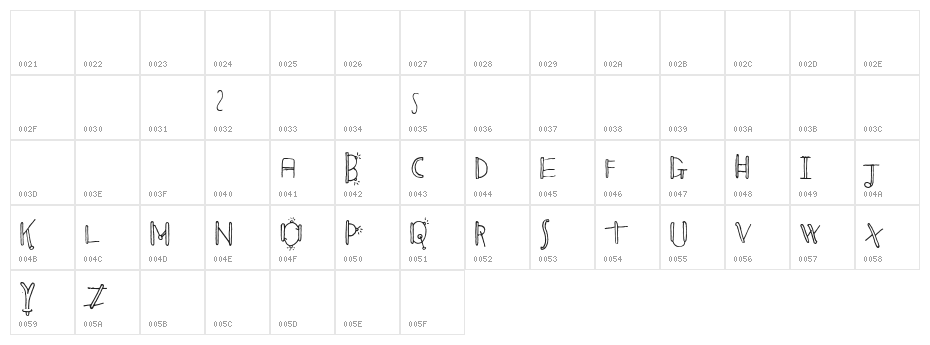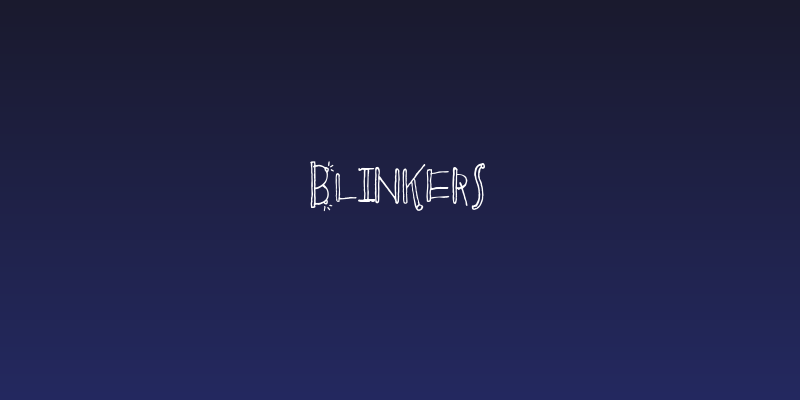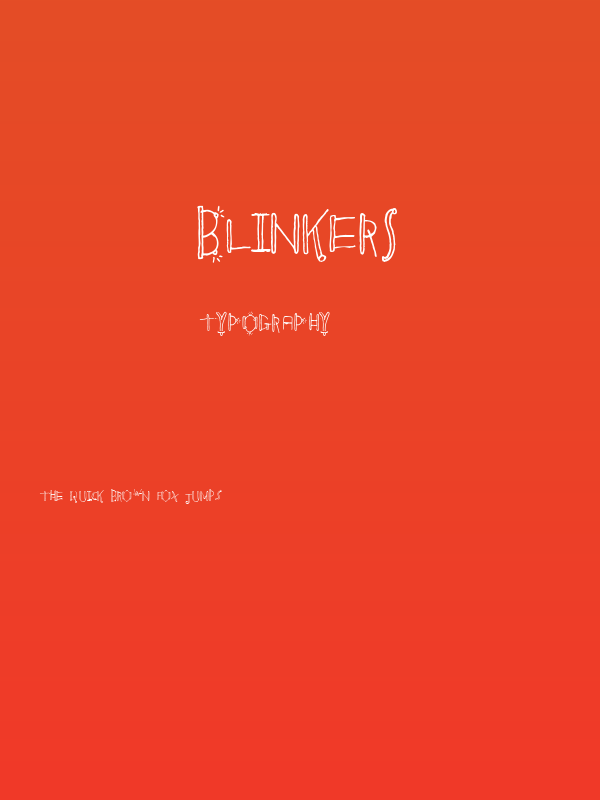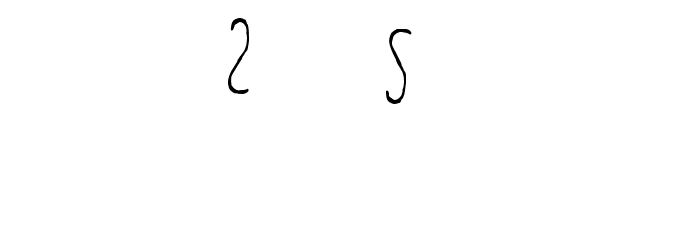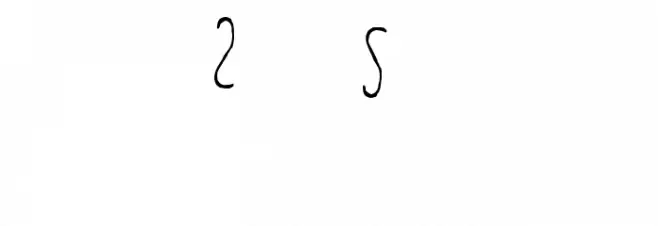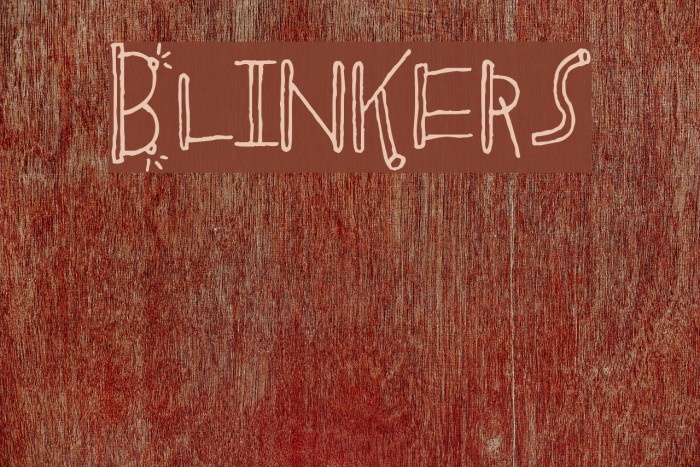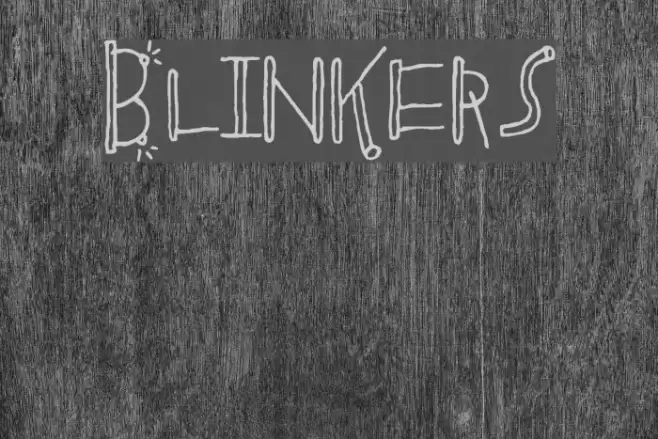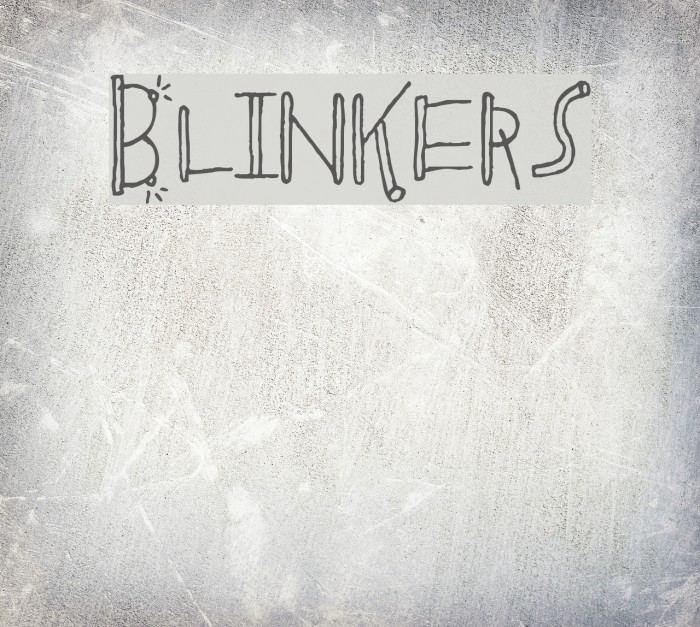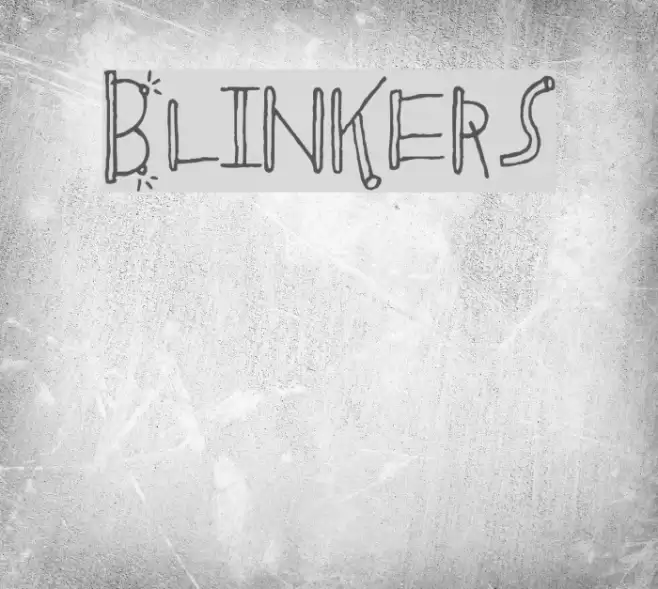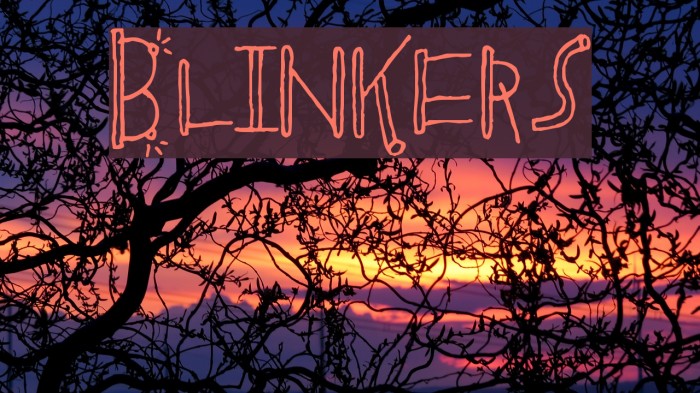
Blinkers Font
✎ Outline
| Kategorien | Outline |
| Gesamtstil | Whimsical, Artistic |
| Anwendungsfall | Headlines, Artistic projects, Informal text |
| Vorgeschlagene Projekte | Ideal for children's books, creative posters, artistic branding, and informal invitations. |